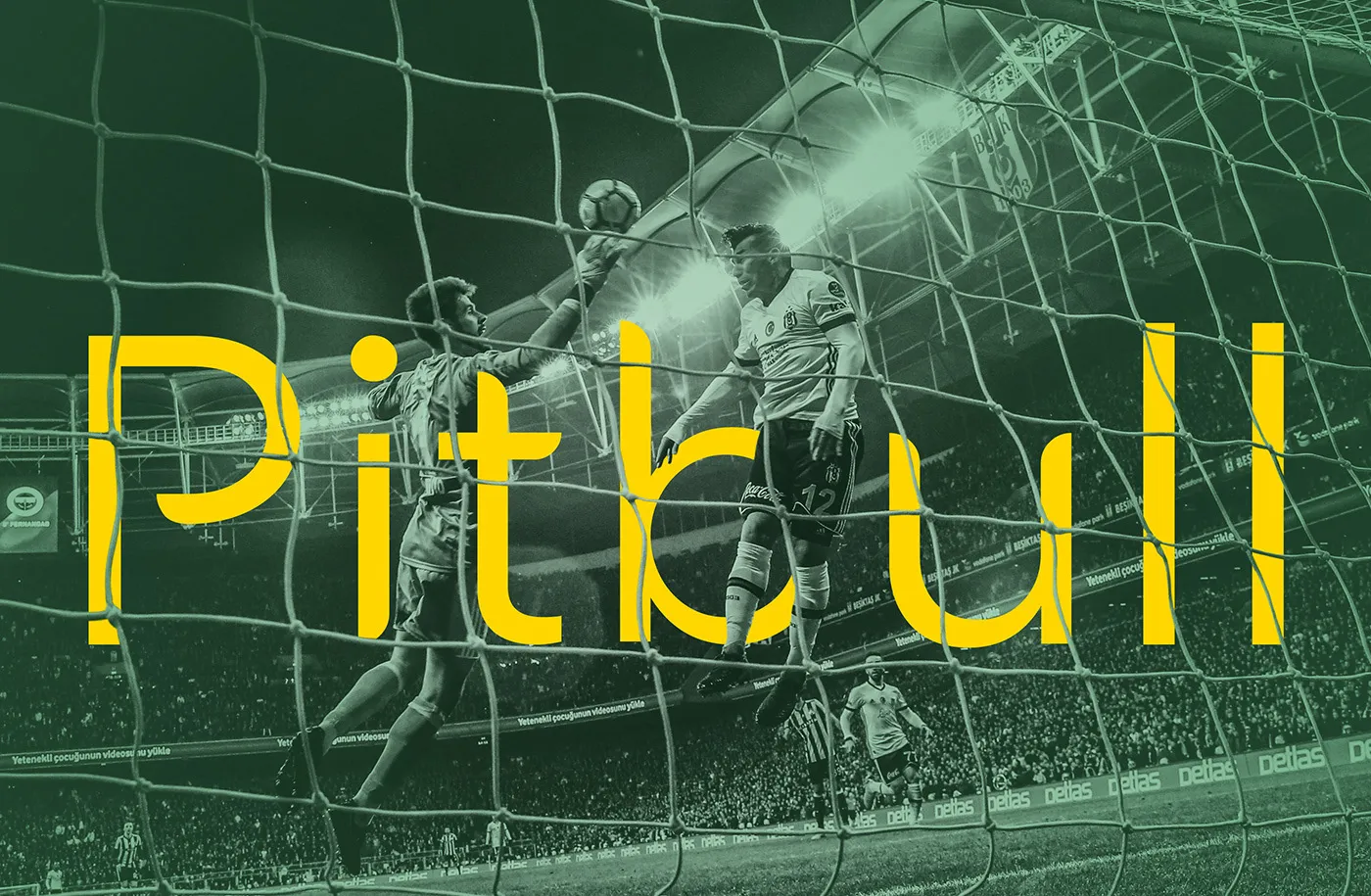
Medel Typeface – Fonte Grátis
Medel Typeface
Medel Typeface é uma escolha perfeita para arquitetos de front-end buscando uma fonte moderna e versátil. Este tipo em exibição foi projetado pelo designer Hamilton, inspirado no ícone esportivo GaryAlexis Medel Soto, um talentoso jogador chileno que atua atualmente para o Besiktas JK. Com seu design clean e limpo, Medel oferece uma variedade de opções úteis em diversos contextos. Seja você um designer gráfico criando layouts impactantes ou um desenvolvedor web trabalhando com responsividade e facilidade de uso, a Medel proporciona o equilíbrio perfeito entre elegância e funcionalidade. Perfeita para aplicações digitais modernas, a Medel também se destaca em ambientes físicos. Seja você um designer gráfico trabalhando com design tipográfico ou uma marca buscando estabelecer um visual forte, a Medel oferece um recurso valioso para qualquer projeto que exija uma fonte limpa e moderna.